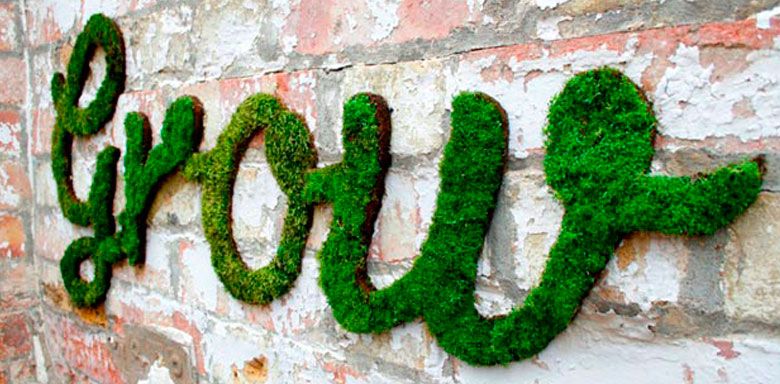
Descubre cuales son las mejores tipografías para el diseño gráfico de tu página web.
“Arte de disponer correctamente el material de imprimir, de acuerdo con un propósito específico: el de colocar las letras, repartir el espacio y organizar los tipos con vistas a prestar al lector la máxima ayuda para la comprensión del texto escrito verbalmente” Así es como define Stanley Morison qué es una tipografía. En websa100, entendemos el diseño gráfico como una comunicación visual y consideramos que la palabra escrita es el medio comunicativo más eficaz en este arte, pero tiene que estar apoyada por su aspecto visual, por eso afirmamos que la elección de las mejores tipografías son fundamentales para el éxito de nuestro diseño.
Parece que este año se están manteniendo las mejores tipografías del 2014, año que podríamos considerar revolucionario del diseño gráfico.
Para obtener las mejores tipografías tener un diseño fabuloso es fundamental, es el resultado de obtener éxito o fracaso, por esta razón es importantísimo dedicar tiempo en la selección de la fuente que queremos utilizar para conseguir las mejores tipografías para nuestra web.
Debemos dar paso a nuevos estilos y no siempre utilizar la típica Helvética o la Gotham, mi recomendación es la de experimentar, ofrecer nuevas alternativas y crear nuevas necesidades al mercado. Realizar algo nuevo puede causar una mejor impresión a nuestros visitantes y diferenciación con el resto de competidores, pero siempre hay que hacerlo con cuidado.
A continuación quiero compartir con vosotros algunas de las mejores tipografías, o que más nos han gustado para este ejemplo, y que hemos estado viendo en este cuarto de año:
Mezcla de Tipografías
Aunque una de las reglas del diseño es no mezclar más de tres tipografías, esta tendencia pisa fuerte desde el año pasado. No es recomendable por norma, pero en esta imagen se ve perfectamente lo bien que ha quedado.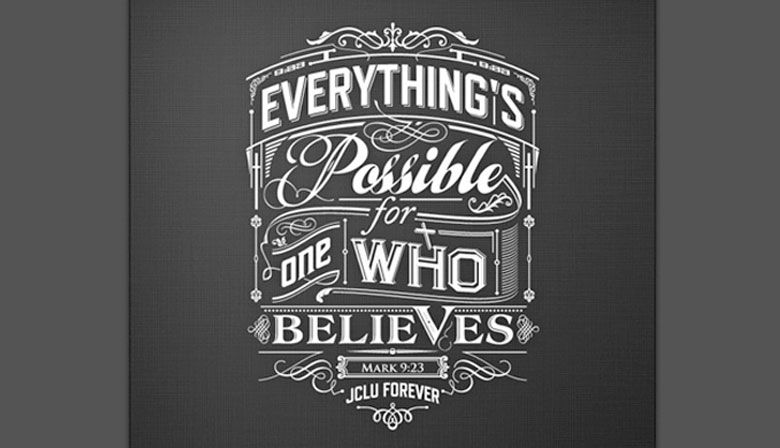
Tipografías tridimensionales
Nos las solemos encontrar sobre todo en páginas web, aplicaciones multimedia y animaciones, en las que el texto se convierte en parte funcional del contexto, da volumen y cierto juego visual de perspectiva. Y como puedes ver da mucho juego para dejar volar la imaginación.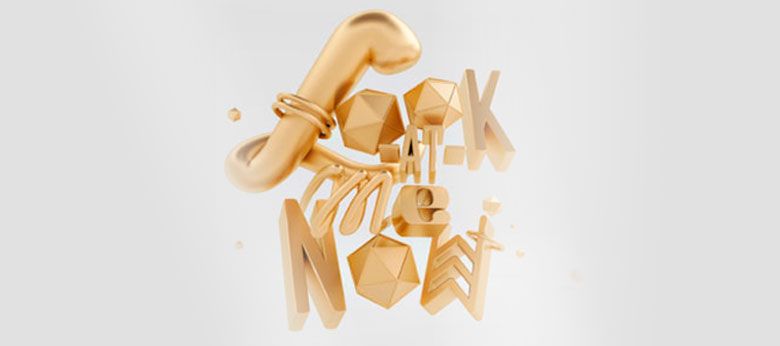
Tipografías con textura
Este tipo de fuentes permite a las marcas mostrar sus productos de manera diferente. Se les da otro valor y el espectador lo conoce sin tener que probarlo. Son las mejores tipografías para aportar una sensación al usuario que las visualiza.
Tipografías de líneas rectas y sin sombras
El flat design seguirá siendo tendencia de este año. Esta tendencia reside en utilizar la simplicidad en los diseño y elimina todo aquello que no aporte valor al mensaje. Los colores sólidos, así como bloques rellenos permiten un juego con el espacio negativo en la tipografía.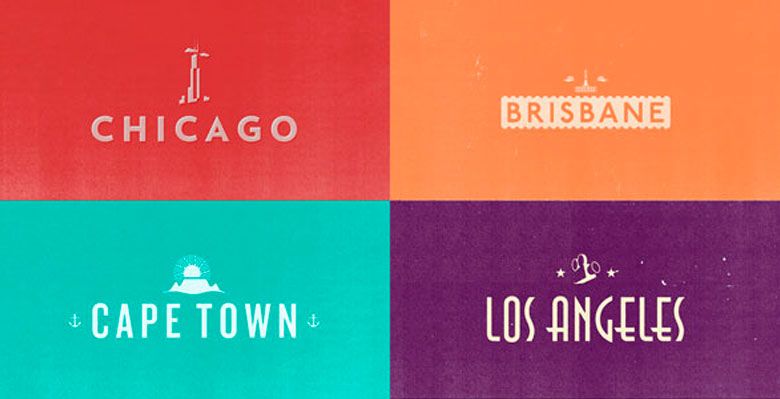
Tipografías hechas a mano
Lo bueno de este estilo es que aporta total exclusividad, nunca verás una fuente hecha a mano idéntica a otra, ya que el dibujante crea plasma su propia identidad en las letras. Destaca como una de las mejores tipografías que no pasan de moda.
Y ahora haciendo referencia a estas últimas, os quiero presentar un proyecto que he encontrado navegando por la red y que me ha encantado.
Homeless Fonts es una iniciativa de la fundación Arrels en la que se une la solidaridad con el diseño. Consiste en crear tipografías a través de la letra manuscrita de personas que viven en la calle, letras que encontramos en sus mensajes escritos sobre cartón. Estas tipografías las puede comprar cualquier persona o marca para utilizarlas en su comunicación. Y el gran objetivo de esta iniciativa es que todos los beneficios obtenidos vayan destinados a ayudar a las más de 1400 personas que la Fundación Arrels atiende y que no disponen de las necesidades básicas que todos queremos. [Tweet “#Tipografías con fondo social”]
¿Cómo se desarrollo el proyecto?
Para crear las tipografías hicieron un taller dónde los autores de las letras y un grupo de tipógrafos colaboradores escribían los abecedarios. Completaban una plantilla a mano con todas las letras, números y signos, para después pasar por un proceso de digitalización hasta convertirse en tipografías. Los tipógrafos se encargaron de convertir las letras al formato digital sin perder la personalidad de sus autores, un proceso bonito y único al que ha traído como resultado una colección de fuentes únicas y personales que reflejar el carácter de cada una de estas personas que las escribieron. Aquí os dejamos algunas de ellas para que podáis conocer el proyecto un poquito más de cerca y valoréis los resultados obtenidos.
Ahora que ya conoces el resultado ¿Qué decides? Esta clase de tipografías son algo único y solidario que puedes encontrar para tu proyecto web. Y si te gusta alguna ya sabes…puedes comprarla y así contribuirás a ayudar a las personas que las crearon.